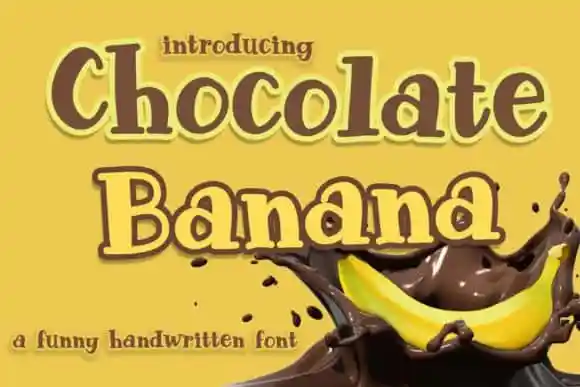
Chocolate Banana Display Font – Download Grátis
A fonte Chocolate Banana Display Font é uma criação criativa feita para projetos de marca e design, com estilo divertido e uma pitada de originalidade. Esse tipo especial pode adicionar um toque único a suas próximas iniciativas. O designer RochArt compartilhou essa fonte única como uma opção perfeita para transformar qualquer ideia de arte em algo realmente inegável. Com seu tom leve e divertido, o Chocolate Banana Display Font é ideal para criar design personalizado, como cartões de agradecimento, cartazes ou logotipos. Sua aparência suave e deslumbrante faz dela uma opção perfeita para qualquer projeto que precise de um toque de escrita manuscrita. Além disso, esta fonte também brilha em cartões de saudação, cartazes e cartelas de negócios. Sua delicadeza e criatividade garantem que ela seja uma escolha atraente para qualquer projeto gráfico ou design de marca. É perfeito para quem busca um toque único sem comprometer o design profissional.